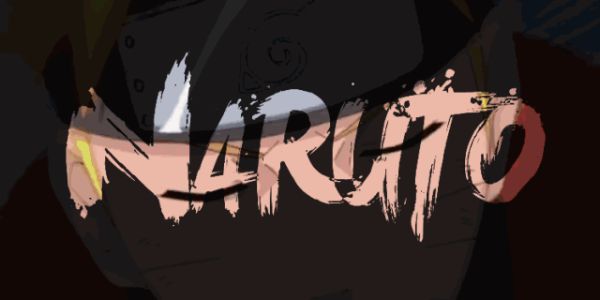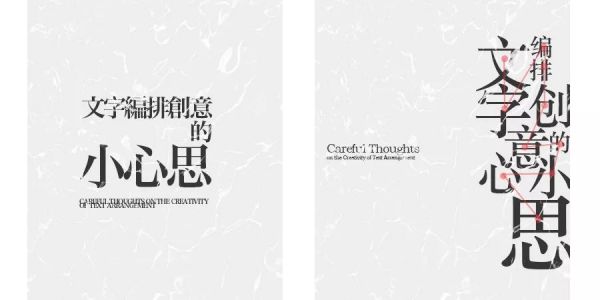
12类艺术字体设计的造字方法
我是一个运营设计师,日常工作经常需要做字体设计,而我的字体设计又很一般,每次遇到需要造字时都没有头绪,我想能不能总结一套方法帮助到跟我一样的同学,让大家在做字体设计时能够有迹可循。为了写这篇文章我研究了数以千计的案例,试图去提炼字体设计间的共性,共总结出12类造字方法,以方法论为主,详细介绍字体设计的整个流程环节。本篇更侧重于艺术字体设计,多适用于活动、海报、banner等快消式设计,不需要经过历史和时间的检验。
QQ阅读团队的两个H5专题头图设计,相得益彰的字体设计会使专题画面更具张力和感染力
一、造字准备——「忘」
造字之前首先要干什么呢,当我们接到一个项目需要造字时,首先深吸一口气,然后闭上双眼去忘了去要造的字。忘掉字体的「点」、「横」、「撇」、「捺」、「钩」、「折」、「提」,忘掉字体的偏旁部首,只把造字当做为一种线描icon的绘制。
首先明确一点字库设计和字体设计是两回事,我们需要尊重字库设计,但本篇更侧重于艺术字体。
我们的目的就是要让单调而无情的字体,通过我们的设计变得与众不同、而又新颖夺目。
二、造字三层面
本质来看,字体设计可以拆分为这3个层面:
字体骨架设计:不同的字体有着不同的骨架,字体骨架影响着字体的辨识度,骨架是一个字体最重要的视觉呈现。
笔划特征设计:笔划可以想象成图形,图形会有不同的表现特征,比如宋体字笔划收尾处的菱角特征,书法字体的飞白特征等等。
留白空间设计:字体的笔划穿插之间会产生不同程度的留白,留白空间的设计影响着字体的透气度,是字体设计中非常重要的一环。
三、造字步骤
1)氛围考究(防止跑题)
主要是针对我们拿到的需求场景,有一个大氛围上的预判,是童趣风、文艺风、还是古代风等。如果没有灵感我们也可以打开花瓣、站酷等平台搜一些比较好的字体设计,找一些跟我们需求感觉比较吻合的字体形式。
2)草图绘制(骨架探索)
下图为站酷大触「左佐工作室」所画的草图,不要怕丑,草图的目的是对字体的不断摸索过程。此处不需要去扣细节,主要是对字体骨架的探索,细节上我们在软件复现时候再去研究。草图绘制主要研究字体笔划的变形、组合方式、粗细长短等。
3)软件制作(精细优化)
此阶段主要是把上一步选中的比较不错的草图骨骼进行电脑图像化,我们可以将草稿拍照然后导入到计算机中,使用软件勾勒出草稿的形体,再去细微调整字体的大小、结构和留白空间,以及字体笔画特征上的设计。(软件的选择上建议使用llustrator CC2015版本或以上版本,AI 2015以上版本新增了圆角优化功能,很方便字体细节的后期处理和加工)
四、造字秘籍
造字秘籍围绕3种类型展开,分别是针对笔划变型变化的【笔划类】,针对字体变形的【字型类】,针对后期修饰加工的【修饰类】。
第一式 断笔(笔划类)
断笔,顾名思义即是对笔划结构的省略和断开,通过在一些转折处、或笔划交接处,适当的断开,可以使笔画更加清爽。断笔后会有不同程度留白,产生新的节奏感和即视感。断笔的基础和前提是充分利用「格式塔心理学」中的封闭性原理。
「封闭性原理」即是人们在观察熟悉的视觉形象时,会把不完整的局部形象当作一个整体的形象来感知。但如果局部形象过于陌生或简略,则不会产生整体闭合联想,所以断笔的级别在于对一个度的掌握。
常见的3类断笔形式——【十字交叉断】【拐角断】【面条断】
十字交叉断:字体笔划之间往往存在交叉,在一些十字交叉的地方进行断开。
拐角断:字体笔划往往会出现拐角状的笔划,通常我们在拐角处进行断开。
面条断:如果把一些修长型笔划看做面条,断笔可以断在面条的任意一个位置。
我们以「日」作为单字的某个部首去做分析,寻找十字交叉与拐角
第6个日是断的极端表现——「省」,特定场合的字组里是经常出现的。
下面例子中,「黄圈标记」是在笔画衔接处断笔,以此提高字体的个性和透气度,「红圈标记」是断笔后的重新组合,应用到我下面要说的第二式「连笔」进行新笔画的重新组合连接,使字体不再局限于单纯的断笔而又产生新的节奏感。所以断笔后会产生新的笔画形式,新的笔画形式可以用我后续提到的其他招式进行进一步改造。
第二式 连笔(笔划类)
「连笔」是指字体间通过分析字体间的笔画结构特征,寻找到字体间可以通过变形而产生连接的结构形式。在保证字体识别性的基础上,大胆去尝试你所能想到的任何可以产生连接的方式,打个比方你要从河一边过到另一边,可能的方法有千千万种。
常见的3类连笔形式——【字内连接】、【字外连接】、【特殊连接】
字内——延长连接:
字体内部笔划进行延长与其他笔划延长笔划产生衔接。如上图「胡同里」的「同」字的折勾延长与同字相交,形成连笔。
字内——旋转连接:
字内笔划旋转一定方向后与其他笔划产生衔接。如上图中「胡同里」中的「里」字的一个笔划逆时针旋转与上侧笔划产生衔接。
字内——断开连接:
字内笔划局部断开,断开区域过延长或旋转与其他笔划产生衔接。如上图中「度假」中的「度」字,部首「又」左上角进行断开,断开后与下侧笔划产生衔接。
字外——顺势连接:
顺势连接多为横笔,斜笔(因为竖笔易使产生上下拉伸的视觉感,会有重心不稳要倒的错觉…)两个笔划位置相近,笔划的倾斜度也相似,可以顺着笔画的走势延伸尝试相交,如若相交不自然可产生适度变形处理。如下图中「空格」和「秒速五厘米」。
字外——错位连接:
当顺势连接不易实现或想在顺势连接的基础上有所突破,可以考虑错位连接,就是把字体位置错开重新排列组合,错开后通过对笔划的延长、旋转、断开等方式创造连接可能,错位方法可参照后面的「错位组合」招式。如下图中「跨年盛典」和「儿童节」。
特殊连接——笔锋连接:
以上连接方法都是以笔划结构出发去做笔划上的连接,而另类连是我见了很多字体以后发现,有一些连接形式不基于笔划结构,同时又会产生笔画连接的效果。我将这些方法汇总归类为另类连。暂举一种常见的——笔锋连接,篇幅有限,后续会再做补充。
我们日常写字的时候经常会不自觉的连笔,而我们却经常不以为意,连笔笔锋准确的说应该属于毛笔字的范畴。我们将笔划以笔锋形式进行连接,并不会奇怪反而会增加字体不一样的动势。
第三式 笔划化形(笔划类)
当笔画进化到形的状态,就偏离了笔画的基本特征,趋近于图形表现。也就更倾向于前面我们提到的做一个「字的icon」的说法。
「笔划化形」通常将单个笔画或部首以图形替代,亦或是字组里面嵌入形状。形可点题并强调字意,亦可做为装饰处理,形不再属于传统字体的「点、横、撇、捺、钩、折、提」的范畴,所以引入形即能打破传统的字体的形式,又能产生新的既视感。神说:「要有光」,在字体设计里面,有形即有灵。
化形方法常见有2种——【字意化形】、【任意化形】
字意化形:
提取字组或单字字意,将字意化为具象图形,合理的组合在字体的骨骼中。
如下图《半岛时光》案例中,提取时间的字意,具象出钟表指针的图形,嵌入在「时」中点笔划的位置。
下图《全明星》案例中,提取星的字意,具象出星星的图形,嵌入在「星」字中,替换一部分笔划。
任意化形:
与字意化形稍有不同,任意化形更加全面而不受约束。笔画或部首可根据情景或特点变换为任意形状,可具象可抽象,灵活多变。
如下图《极地大冒险》中的「冒」字处理,将「目」的部首处理成类似一个漩涡的形状,迎合了一种冒险、不断探索的感觉。
第四式 笔划包容(笔划类)
行走江湖总得有个家嘛!「笔划包容」即是将字体进行包容和整合,容可以理解成「房子」,而字体的骨骼则充当房内的家具和摆饰!笔划包容有一个先后顺序是通常我们先设计字体的骨骼,然后再根据字体的骨骼去选择盖什么样的「房子」,方的、圆的、高的、矮的等等…….
此种方法常用在多个字的组合设计中。经过「笔划包容」的字体会显得更加的整体和统一,在一些专题、banner等设计中,「笔划包容」的处理方式会大大提高字体的视觉聚焦。「容」并不是说像个包子一样把字体全部包在里面,而是说使字体具有包容感。
笔划包容常见有3种——【常规「容」】、【描边「容」】、【异形「容」】
常规「容」:
常规性的「容」,即是我们常见的规则几何图形,比如方形、圆形、三角形等。以这些规则几何形状作为「房子」去包容字体。此种方法较为常见,难点在于字体与图形间的二次融合。
具体可以理解成Photoshop中形状工具展开项的前5个与字体间的组合。
描边「容」(反白):
描边可能是我们经常用,而有的时候又想不到的一种方法了。小编将描边也作为「笔划包容」的一种形式,因为描边也同样会使字体产生包容感。
描边「容」进一步细分常见有四种描边形式(可逐一对照以下案例对比观察):
常规描边:常规描边可以在PS里加一层描边图层样式,也可以在Ai加描边,亦或是Ai里偏移路径形成描边感。这里主要讲方法论,不做多说,推荐使用Ai,Ai的描边是可以控制描边后的拐角形状的。
移位描边:区别于常规描边,移位描边是将描边进行一定程度的位移,形成一种「伪立体」感。
异形描边:异形描边区别于普通描边的根本点在于会将描边进行二次创造,虽有描边的感觉,但已不单单图层样式和移动就可以呈现的了。
扩充描边:当描边足够粗就会与字组形成偏离感,通常我们再做一些描点的简化处理,会形成一种「描边扩充感」。
异形「容」:
异形的「容」,顾名思义「房子」可以是千奇百怪,造型各异的。不拘泥于传统,更讲究随心随性,这种形式是无迹可寻的。
以下例子可以发现,「异形容」可以是基础图形的组合,可以是墨迹感的反白,可以是盾牌,可以是曲线的弯曲抖动,可以是立体盒子,也可以是水滴造型等等。这个形式更考验对字体的理解、造字的经验和想象创造力。
第五式 笔划生枝(笔划类)
「笔划生枝」意思是说如果我们将笔划骨骼比作树干主体,那么树干上可以伸出来各样的树枝,这样的枝干会显得更加的丰满,细节更加的完整。比如下图中两个字分别是微软雅黑(左)、宋体(右)的字库字体,雅黑字体横平竖直,而宋体字在笔划上却有很多细节特点,这就是一种「笔划生枝」的手法表现。
而「笔划生枝”方法中的重点就在于」枝「的表现上。「枝」可以从枝干的任何一个部分分枝发芽。既可以向外生「枝」也可以向内生「枝」。而「枝」的形状、粗细、曲折就会带来不一样的视觉感受。
笔划生枝常见有2种——【局部生枝】、【嫁接生枝】
局部生枝:
局部升枝是最常见的表现形式,通常在笔划的初始端或末尾端去做生枝处理,在字体的提笔、顿笔、折笔处和字体组合时的大留白处进行相应的各种形状的「生枝」。而生枝时应尽量保持统一性,不易多于2种「生枝」形状。
如下图中的一些局部小细节处理,会显得很精致~
嫁接生枝:
「嫁接生枝」即是将枝干进行大幅度的延伸,形成一种在字体主要枝干基础上进行嫁接的感觉。
如果说「局部生枝」是短而小的,那么嫁接生枝便是长而大的。对于字体枝干上的延伸嫁接会使得字组有一种外放的扩张感。
第六式 笔划融合(笔划类)
「笔划融合」说白了就是填坑,主要针对于两种类型字体。
1)有一些字的某些笔划呈现包围或半包围结构,比如部首「口」「日」「目」等常见的结构。
2)亦或是某些字笔划比较多,书写繁琐,同时要兼顾上下左右结构,比如「繁」「聚」等。
通常针对这两种类型字体,可以忽略一些内部笔划结构将笔划融为一体,形成一种下面例子中的感觉,小编找到的例子都做了统一色调处理,采用此种功法的字组建议慎用黑色,此种功法配黑色看久了会显得比较压抑。
第七式 透视大法(字型类)
前面讲过的所有方法都是在二维平面去做设计,而所有字体的应用场景也都是在平面二维视觉中。「透视大法」是说在字体设计中通过字组之间的堆叠,或者是字体笔划的纵深处理,使得整组字体呈现出一种透视感,或者称之为一种「2.5维动感」。
在进行「透视大法」之前,需要明确字体的透视透视原理,是在二维平面上产生消失点,形成一种近大远小的错觉。通俗的讲,「透视大法」可以理解为是将传统笔划的横平竖直变为「一头大一头小」的字体形式。
透视大法常见有3种——【笔划透视】、【单字透视】、【组合透视】
笔划透视:
笔划透视是指在字体的横笔、竖笔、提笔等笔划上创造透视。笔划呈现出「一头大一头小」的特点,也就是说如果我们去延伸这种「大小」的走势,会产生一个消失点,这就是【笔划透视】。
*笔划透视常伴夸张,有时不妨在透视的基础上加以夸张,或许会有意想不到的收获。
单字透视:
单字透视是指把字组中的一个字作为「形」去创造透视,可以想象成ps中的Ctal+T的自由变化,形成不同方向上的纵深透视。
组合透视:
组合透视是说当我们去创造字体组合时,将整个字组作为一个图形去做透视处理,字组透视同样可理解为一头大一头小…….
值得注意一点是,字组透视常会伴随某些字体偏小,在做处理时,尽量避免偏小字体笔划过多而堆积在一起。
第八式 借用繁体(字型类)
在进行字体设计时,有一些字造型比较简单,比如下图例子中的「式」「记」「风」等,而我们又想不到其他的变形手法,这个时候不如去尝试一下去「借用繁体」这个方法。
绝大多数汉字都是存在繁体的,而现在的字体也都是经过繁体阶段简化而来。所以「借用繁体」是对时间的一种追溯,所以在视觉呈现上容易给人一种怀旧感、时代感、历史感。
此功法不做多说,主要是对个别字进行简化繁体的处理,很多时候我们可能想不到这个方法,但是这个方法又相对比较简单又容易出彩的方法。
第九式 反笔妙用(字型类)
「反笔妙用」是一种逆向思维方式的表现,一个字的某个笔划书写次数多了就会形成固化思维。而此时如果我们将某些笔划进行反向处理(可以理解为ps中的水平翻转和垂直翻转),就会有一种耳目一新、眼前一亮的视觉感。
「反笔妙用」多针对字体的局部点缀性笔划和一些倾斜性笔划进行变形处理,「反笔妙用」方法属于偏后期的处理手法,因为进行反笔后的字体不会有大程度的颠覆性变化。
第十式 错位组合(字型类)
「错位组合」此种方法应用也是比较多的,此方法可以拆分为两招(可不是一阳指和狮吼功….)。
一为「错位」、二为「组合」,我们进行逐一分析:
错位:
常规的字库字体为了整体的协调统一,多为方方正正的笔画部首组合,所以首先我们要应用第一招「错位」破开方方正正的部首组合。如下图所示(矩形代表部首):
组合:
组合是说字体的组合方式,常规的惯性思维我们常将字体进行较为规整的横向或竖向排列,这是一种固有思维需要打破。
打破方式就是将字想象成积木,字会限制组合的思维,而想象成积木你讲有无限发挥的可能。
以下都为小编的任意举例,主要为了说明组合的方式千千万,不要局限横竖两种。
错位+组合:
通过以上我们说到的「错位」「组合」两招合二为一就是错位组合这门武功的真谛了。
下面是应用错位组合的一些字体设计案例。多补充一点是错位连接易产生部分空荡部位,常用英文、拼音、或一些装饰进行补充丰富加强。
第十一式 氛围装饰(修饰类)
「氛围装饰法」是指通过为字体的周围增加抽象或具象的装饰物,使得字体在原有的笔划造型基础上能够有更加丰富的视觉表现。装饰物的选择上没有过多约束,尽量贴合字意,如若不易找到贴合字意装饰物,尽量使用抽象图形式装饰,另许注意「氛围装饰法」中的装饰物通常对字体周围进行装饰,这样不会因为装饰物对内部笔划的遮挡而影响辨识度。
装饰物常见有4种——【图形装饰】、【字母装饰】、【写意装饰】、【全局装饰】
图形装饰:
顾名思义,图形装饰的装饰物为图形,常见的有三角形、圆形、分段矩形、曲线等,图形装饰最是简单高效易出效果。
字母装饰:
装饰物为字母,英文和拼音都属于字母装饰,我们国人的第一视觉捕捉一定大号中文字体,小而点缀性质的英文或拼音就自然充当了辅助装饰作用,最为常见的就是利用字母装饰填补字组变形所产生的空白区域,此种方法也很常见,通常添加字母装饰的字体会显得更有逼格~
写意装饰:
写意装饰是指装饰物不再抽象,而是更加的具象化而产生一定的含义,如下面案例「药不停」中的写意装饰是一个打开的胶囊,「石榴汁」中的写意装饰是从「汁」上滴下来的一个小水滴,「小野」中的写意装饰是水面蜻蜓点水状的涟漪。
全局装饰:
全局装饰是以上三种方法的融合进阶,无迹可寻,需要很强的创造力和想象力,装饰物与字体之间的融合度很高,这种方法在专题活动中最为常见,也是最难的一种装饰方法。
第十二式 借位让位(修饰类)
「借位让位」着重强调的是笔划之间的互补,在多个字的字体组合结构中,因为每个字体的大小、变形、和排列形式的不确定性,字与字的靠近区域会形成各种各样的断开空间。「借位让位」即是将这个断开空间顺着笔划的走势进行一定程度的变形处理。使这个断开空间呈现一种似断非断的连接。
此种方法是一种后期细节处理方式,是后期处理中最为出彩的一种方法,经过「借位让位」的字体视觉上会显得更加整合与统一。
五、秘籍汇总
六、尾话